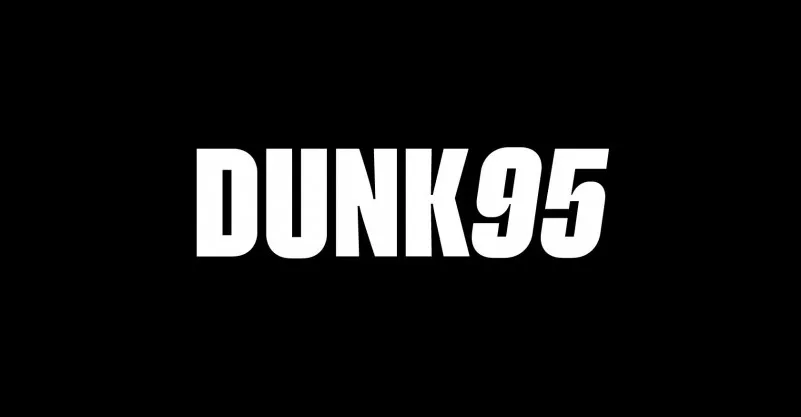
Esse é um projeto moderno e elegante, a Dunk95 Sans Serif Font traz uma mistura única entre serif e sans-serif, criando um estilo geométrico que mantém seu charme sofisticado, mesmo incorporando alguns toques de estética retro. Desenvolvida pelo designer Hamilton, essa família de fontes é perfeitamente adaptável para diversos tipos de projetos gráficos: desde layouts de exibição inovadores até logotipos criativos e até conteúdo textuais extenso. A Dunk95 Sans Serif oferece uma aparência limpa e contemporânea ao mesmo tempo que carrega um toque nostálgico, fazendo-a perfeita para qualquer aplicação da sua criação. Um verdadeiro equilíbrio entre modernidade e elegância, ideal para designers de todo o mundo.